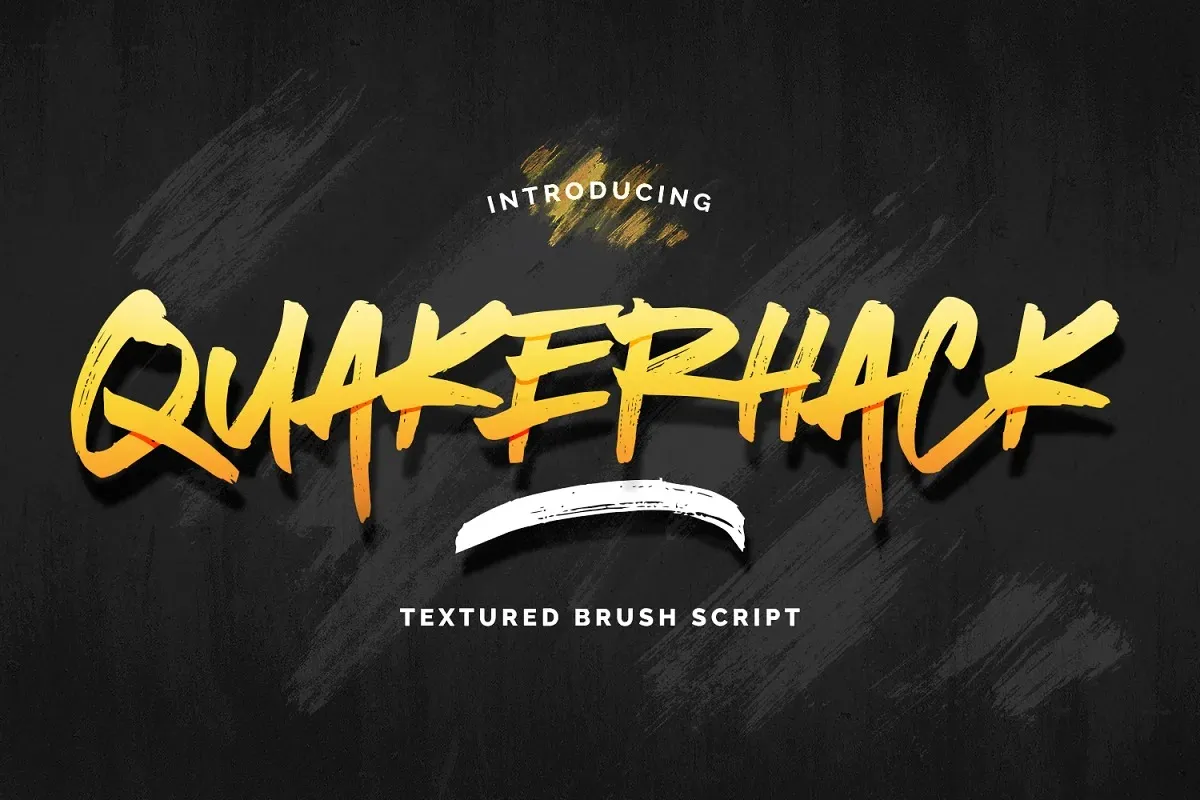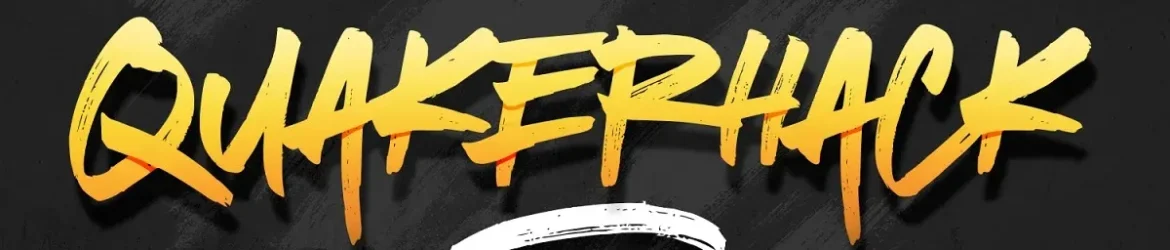
A Quakerhack é uma nova fonte brush script criada pela Almarkha Type, com traços de tinta fortes e uma escrita erguida e divertida, que adicionam um toque de ligaturas para dar uma certa personalidade à família de letras. As letras são feitas com pincéis no Procreate, depois são scans e cuidadosamente desenhadas em formato vetorial. Isso resultou na Quakerhack com seu charme autêntico e relaxado que dá um aspecto natural a sua escrita, melhorando o apelo visual de seus textos. A fonte inclui uma variedade de alternativas e sublinhados que tornam os textos mais interessantes. É perfeita para projetos de design de móveis de casa, criação de marcas, criação de logotipo e embalagem de produtos de marca. Com um painel Ligature OpenType ativado, você pode experimentar diferentes estilos da fonte, mantendo o estilo natural que faz dela uma excelente escolha para a criação de design gráfico moderno e autêntico.